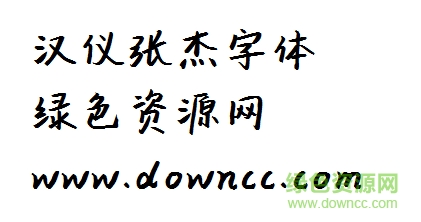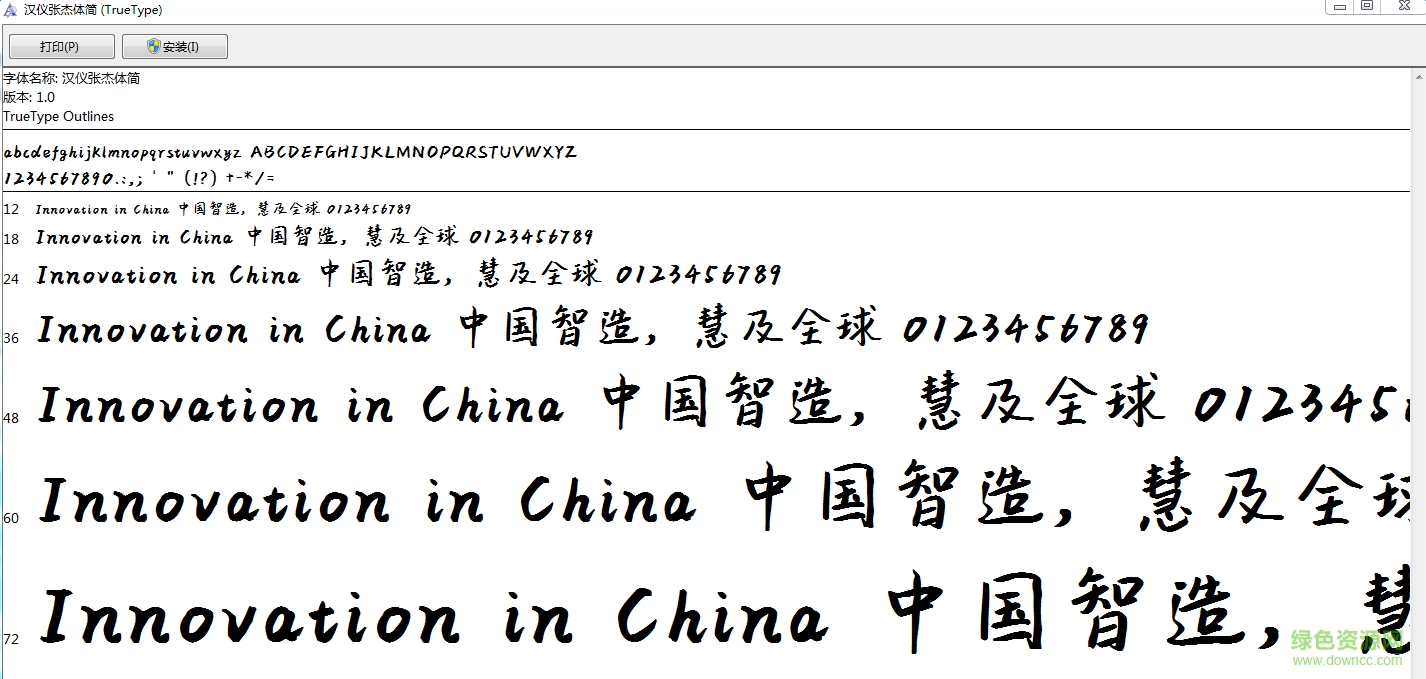
漢儀張杰體字體是一款漢儀類張杰字體軟件,張杰的字體給人非常豪放的感覺,深受廣大年輕人的喜愛,還有更多好看字體盡情期待,歡迎到綠色資源網(wǎng)下載體驗(yàn)!
張杰的字曝光后,清秀、小巧的字體得到好評(píng)。就在近日,其字體被漢儀字庫收錄。在張杰以往詮釋的角色中,男子氣概十足,小編此次給大家?guī)淼氖菨h儀張杰字體。